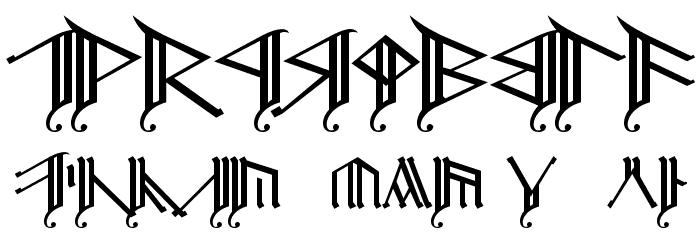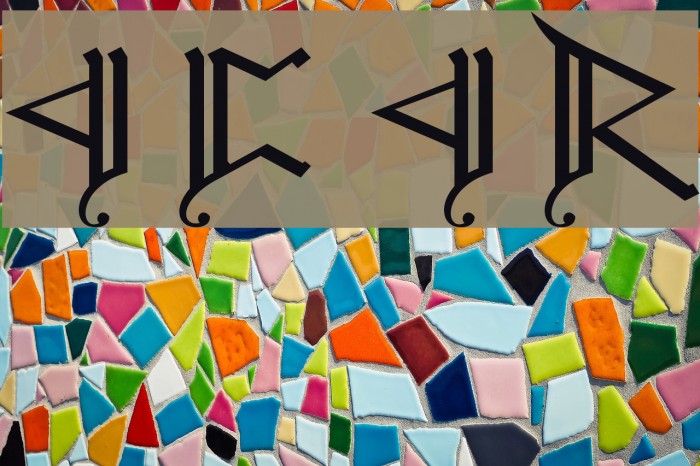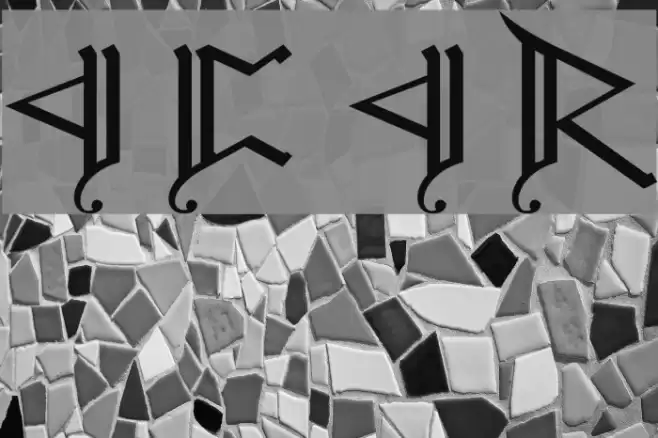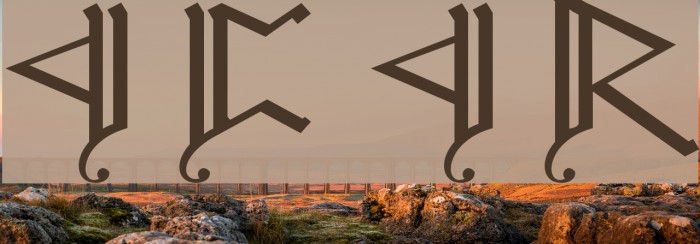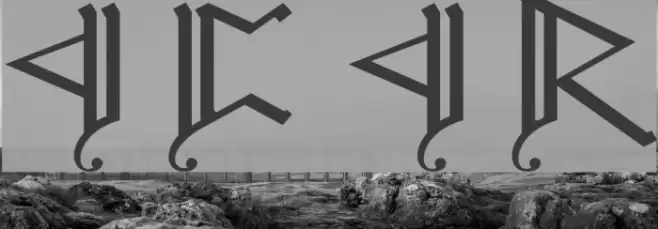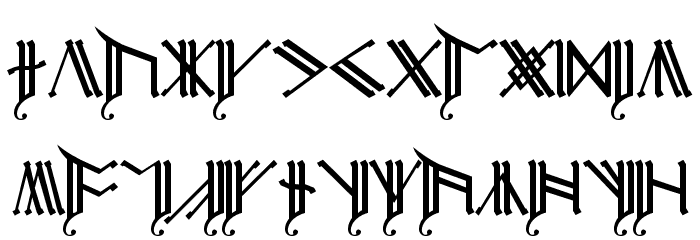
Cirth Erebor Caps 2 Font
| Projetos propostos | Ideal for fantasy novels, themed events, role-playing games, or any project requiring a historical or mystical touch. |